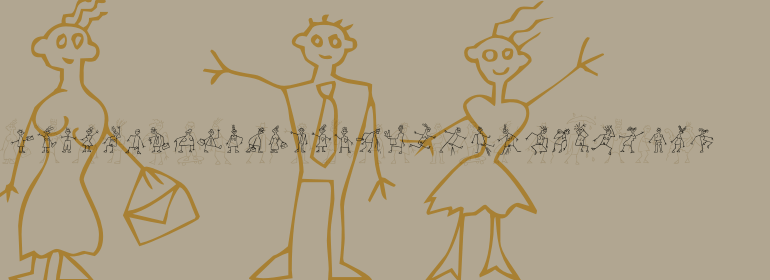
Linotype Monday Devils™
Linotype Monday Devils™,这款字体结构工整、笔画清晰,兼顾美观与易读性,适用于标题、正文、海报、包装、LOGO 等多种场景。字形优雅稳定,风格百搭耐看,适配日常排版与创意设计,让文字呈现更舒适、更具质感。Linotype Monday Devils™一笔一画,皆是细节,以均衡的比例、流畅的线条打造舒适视觉体验,字形端正大气,风格简约现代。无论是商业设计、品牌宣传还是日常排版,都能轻松驾驭,让文字更有格调与力量。Linotype Monday Devils™字体下载。
字体品牌: Linotype(Monotype) 设计师:Herz,Jörg 字体分类:衬线体 字体属性:外文 字符集:Unicode 发布时间: 2018